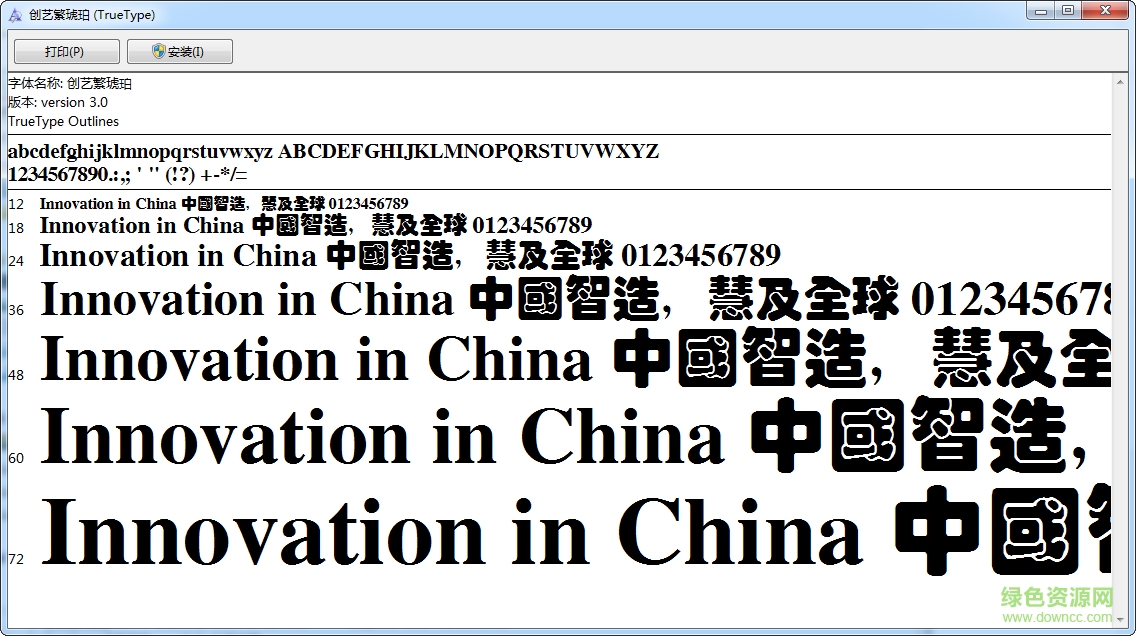
cthuposf是什么字體?字體cthuposf就是創(chuàng)藝繁琥珀,這款創(chuàng)意字體和彩云體很像,外形圓潤(rùn),生動(dòng)靈活,圓潤(rùn)的弧線和飽滿的結(jié)構(gòu)形成一種特有的視覺(jué)個(gè)性,喜歡的朋友快來(lái)綠色資源網(wǎng)下載吧!
狀似晶瑩的琥珀,筆畫粗壯充實(shí),但在重疊處有白線勾勒以示分明。方正琥珀體字型圓潤(rùn)飽滿,新穎活潑,結(jié)構(gòu)錯(cuò)落有序,粗而不重,胖而不臃。